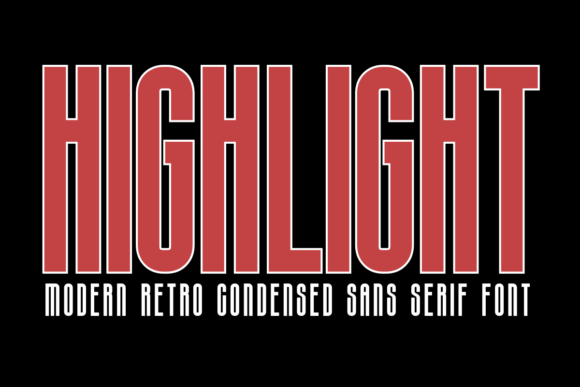
Highlight
Ulasan Lengkap: Font Highlight – Kekuatan Retro Modern dalam Setiap Karakter
Jika Anda seorang desainer grafis atau kreator konten yang memerlukan font yang kuat, kompak, dan tetap elegan, Highlight adalah pilihan yang tidak boleh dilewatkan. Font ini merupakan perpaduan sempurna antara estetika vintage dan kebutuhan desain kontemporer, menjadikannya favorit di bidang branding, merchandise, dan media sosial.
Keunggulan Highlight: Kenapa Font Ini Menonjol?
- Proporsi Tinggi & Strokes Vertikal – Menambah kesan tegas dan mudah terbaca di semua ukuran.
- Condensed Structure – Efektif dalam memanfaatkan ruang terbatas, ideal untuk print on demand seperti kaos, mug, dan tote bag.
- Spasi Seimbang – Membuat setiap kata terasa jelas dan terdefinisi.
- Vibrasi Retro Modern – Terinspirasi dari headline vintage namun tetap relevan dengan tren editorial saat ini.
- Fokus Display Font – Sangat cocok untuk judul, logo, dan headline yang butuh perhatian ekstra.
Use Cases: Dimana Highlight Bisa Membuat Perbedaan?
1. Branding & Logo: Bentuk visual yang kuat memudahkan brand Anda dikenali.
2. Merchandise: T-shirt, hoodie, mug, dan tote bag menjadi lebih menarik dengan karakter condens yang jelas.
3. Desain Editorial: Judul artikel, headline majalah, dan cover buku mendapat sentuhan modern.
4. Social Media Graphics: Postingan Instagram, cover Facebook, dan banner YouTube tampil lebih menonjol.
5. Produk DIY & Cricut: File potong vinyl, label, signage, dan dekorasi DIY menggunakan Highlight tetap tajam dan mudah dipotong.
Kesimpulan: Highlight – Font yang Menggabungkan Kekuatan dan Fleksibilitas
Highlight adalah pilihan sempurna bagi para kreator yang mencari font sans serif yang bold, condensed, dan highly usable. Baik Anda sedang merancang logo, mencetak merchandise, atau membuat grafik media sosial, Highlight memastikan setiap kata tampil dengan kejernihan dan dampak visual yang kuat.